폰트포지+일러스트레이터 드로잉으로 영문 손글씨 가이드
일러스트레이터에서 또는 드로잉 앱, 그리드를 활용하여 영문 손글씨를 써보고 SVG로 출력하여 폰트포지에서 영문폰트를 만들어보세요.
일러스트레이터 대체 오픈소스 잉크스케이프, 폰트포지 이외에 다양한 오픈소스로 나만의 글씨를 폰트로 만드는 프로젝트를 진행하려고 합니다. 물론 영상도 찍고 유튜버로 활동도 해볼생각입니다.
2025 휠캘린더 블랙 비밀의 목표달성
어린이들이 좋아하는 블랙라이트 펜…
올해 만드는 휠 캘린더는 블랙버전이 따로 있습니다.
블랙라이트 조명을 비추면 글자가 나타나고… 사실 내가 얼마나 했는지를 기록하는 용도입니다. 66회 100회 같은 습관 트레이닝용
뭔가 나 혼자만 보고 싶은 캘린더를 만드는 게 목표입니다. 돈을 모으거나 어떤 행사를 기대하거나… 두근두근…
떼어내는 노란색 버전도 준비 중입니다.
블랙은 여기까지
용지 위에 별을 넣을 예정입니다. 조디악
사실 휠 캘린더는 자석과 결합됩니다.
아파트 철문에 붙일 수도 있고
냉장고에도 붙어요
악필교정하는 교정폰트를 생각하고 있습니다.
기존에 쓰시는 글씨를 바르게 쓰면 내 글씨를 바로 잡을 수 있는 기본 폰트를 만들어주는 아이디어입니다. 폰트를 만들면서 또박또박 쓰고 나면 제가 쓴 글씨와는 다른 글씨가 나오는 것을 알게 되었는데 그게 이 프로젝트를 하게 된 이유입니다.
가끔 옛날에 쓴 글을 보면 엉망진창 이었는데 그 원인이 너무 시간없이 아이디어만 기록하는 용도로 써왔기 때문에 점점 알아보기 힘들어졌는데 최근에 글씨를 많이 쓰는 작업을 하다보니 안정화 되어가고 있는 것을 느낍니다. 특정한 운동과 근육량이 늘어나는 작업을 하다보면 글씨가 달라지는데 그 점에 착안을 해서 연령대별로 기록할 수 있는 글씨를 바른 폰트로 만들고 그걸 가이드로 다시 써보는 연습을 하게 하는 것입니다.
모든 일이 그렇지만 반복되어야 잘 할 수 있게 됩니다. 재미있어야 잘 할 수 있습니다. 그 부분에 다른 아이디어를 추가적으로 넣고 바른 손글씨 + 교정폰트를 만듭니다.
지난 두달간 작업한 한글폰트 만드는 서비스를 대충 완성했고. (늘 대충) 그보다 더 많은 이상한 폰트도 만들었고 이번에는 바른 손글씨를 쓸 수 있는 가이드도 작업해서 온라인 손글씨 제작 및 제출하는 프로그램을 하고 있습니다.
어차피 책 구매자 대상으로 폰트를 만들어드릴 생각이라 바른 손글씨 정도로만 일단 만들고 손글씨 제작을 아이패드나 PDF annotation 기능을 활용해서 제작합니다. 굿노트에서 작성하거나 프로크리에이터 등등 템플릿 위에 글씨를 쓸 수 있는 소프트웨어로 작업한 데이터는 모두 처리합니다.
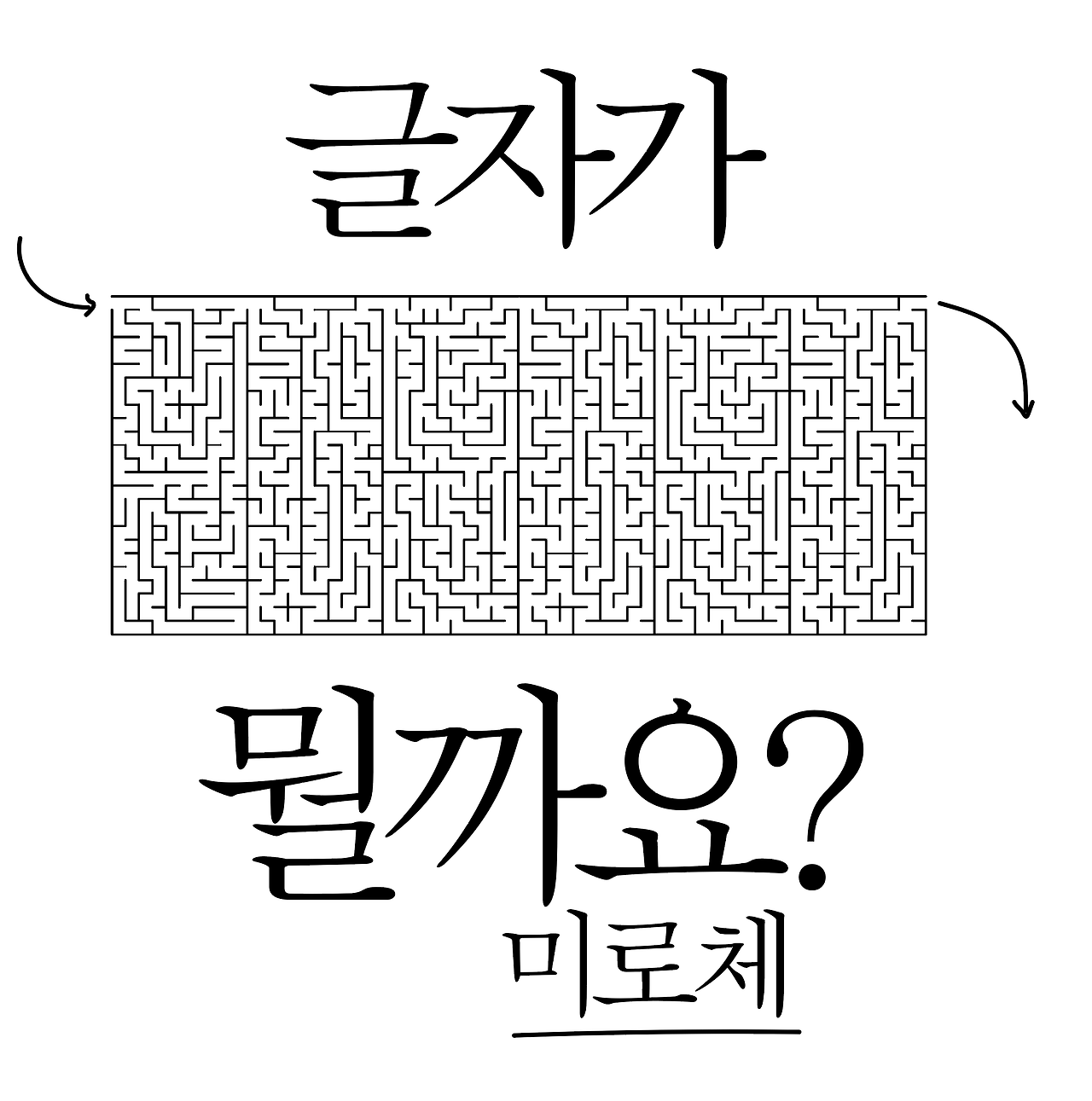
한글미로 찾기 폰트 만들기에 꽂혀서 주말반납했습니다.
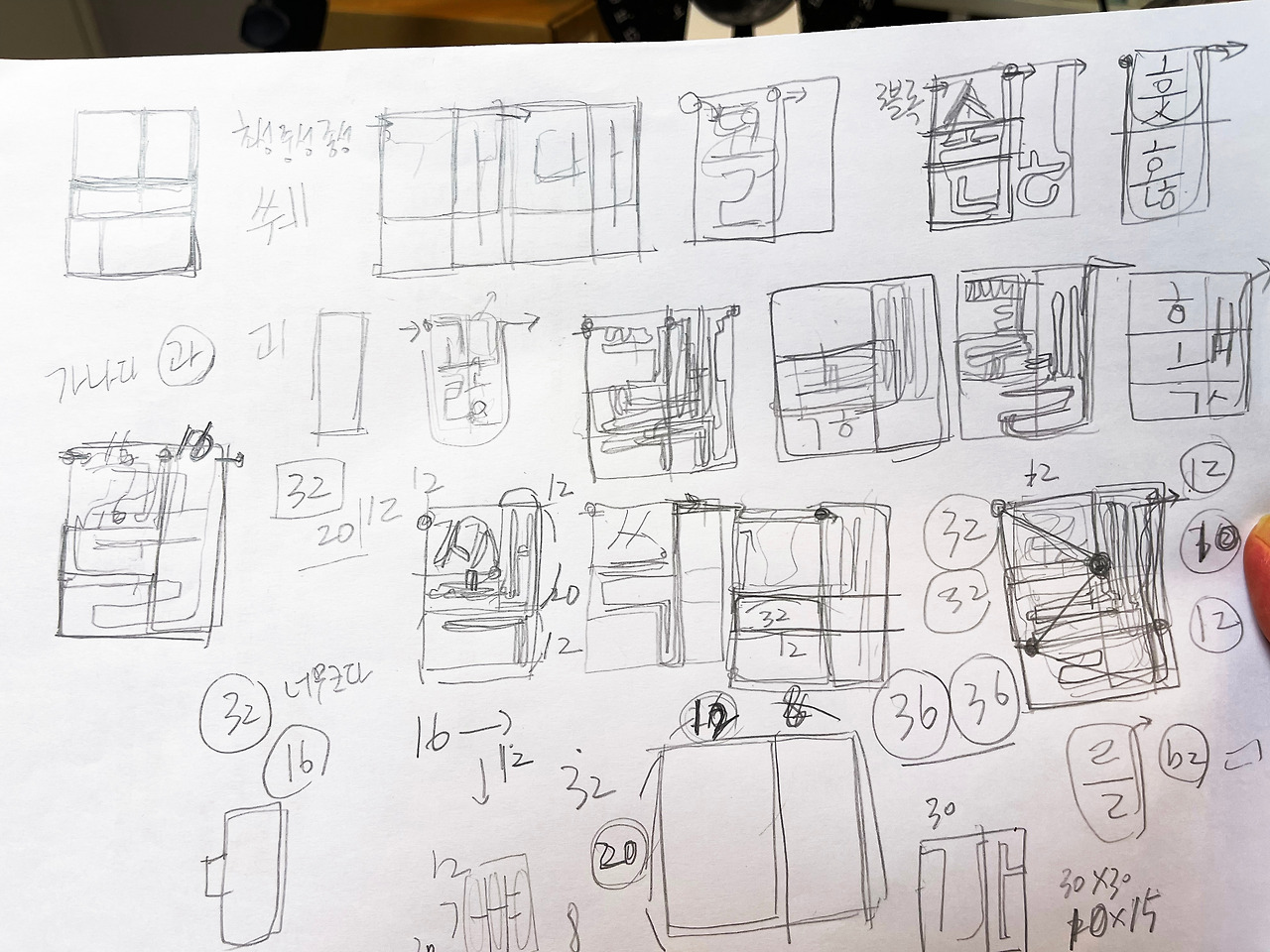
일단 조합되는 글자에 특정한 위치를 연결해서 다음 초, 중, 종성이 특정한 위치로 연결되는 글자구성을 만들었고 너비, 높이를 맞춰서 최소한의 자모를 사용해서 폰트를 만들어볼 생각이었는데… 안예쁠거 같다 라는 생각으로 다시 사각형으로 맞췄습니다.
a9미로체 폰트패밀리에 실제 폰트로 구성한 미로스타일도 준비하고 있습니다.
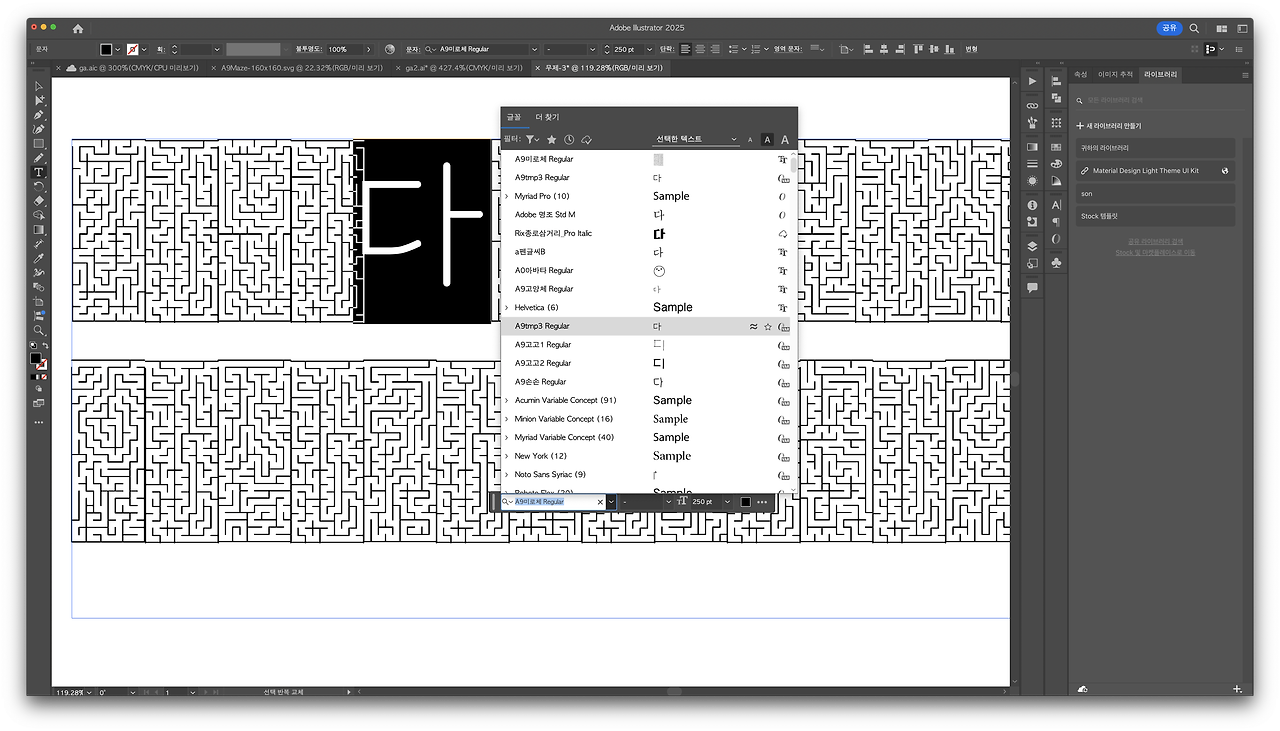
그냥 일반 한글 폰트로 바꾸면 다 자가 나옵니다.
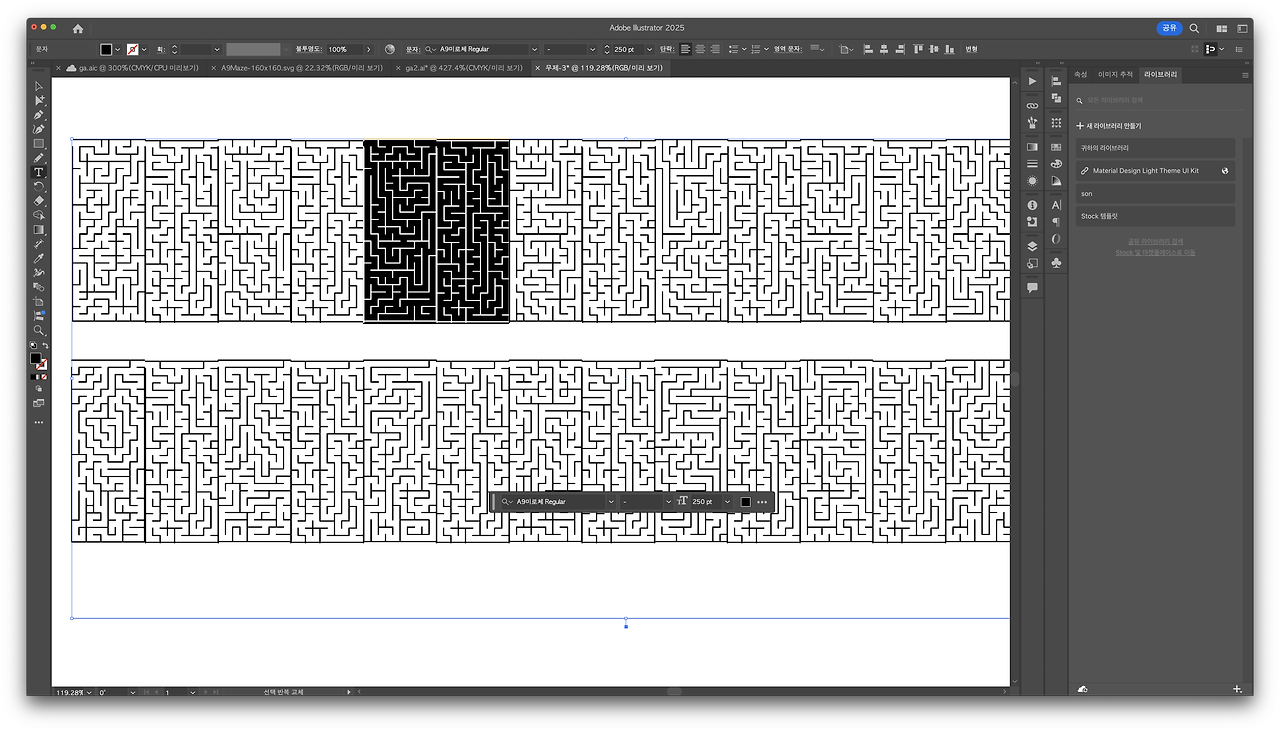
가나다라~ 하 이고 진짜 주말 날림
아주 정확하게 좌표를 잡으면 병풍느낌이나 반전했을 때 도장느낌의 글자가 될거 같습니다.
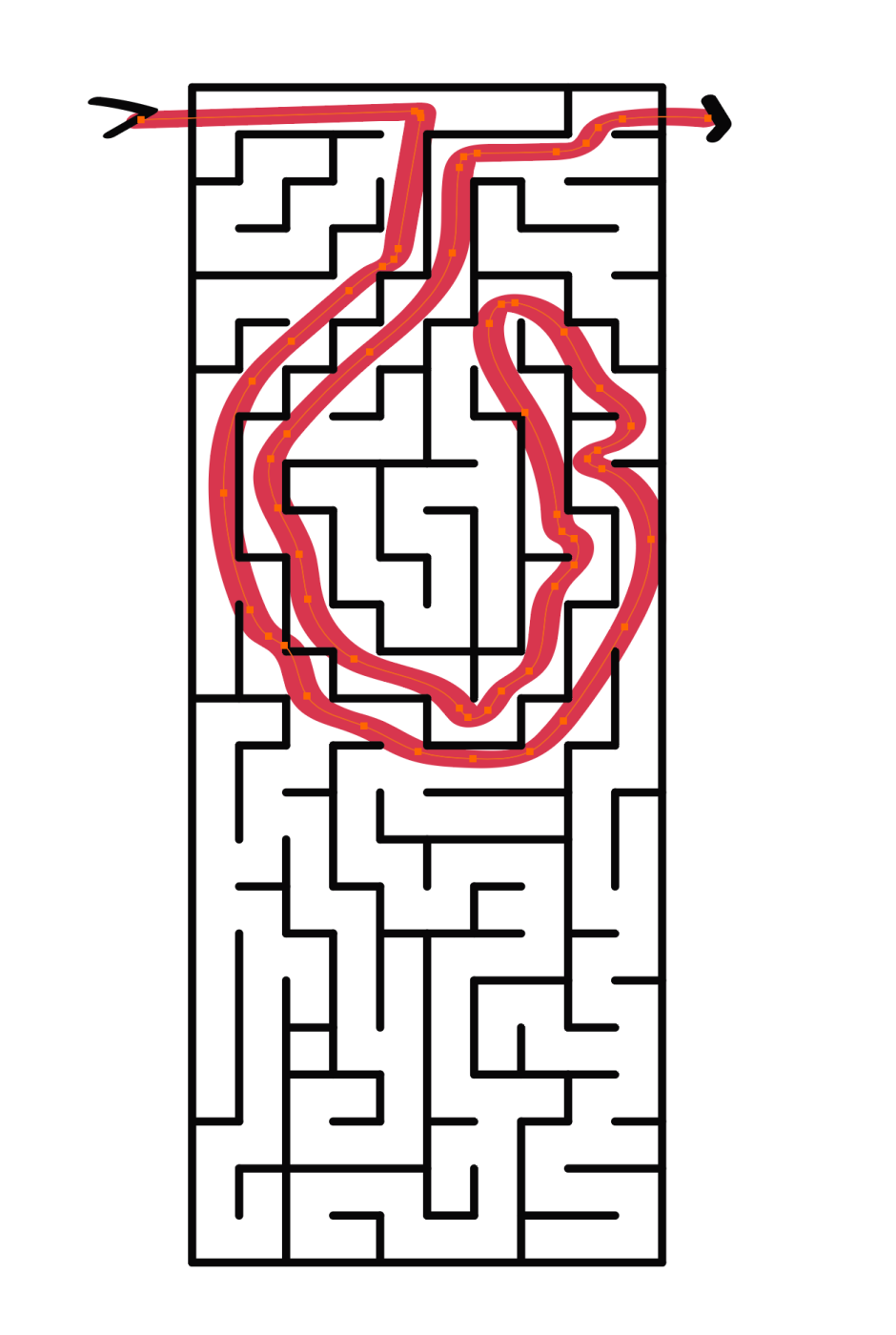
미로를 지나가서 통과하면 지나간 부분에 글자가 나타납니다. 길은 한개 앱으로 만들어서 키워볼만은 할거 같지만 지금은 먼저 다른 일부터
생각하고 프로토타입까지는 금방하지만 결과물을 위한 완성도는 아예 다른 작업이라 어린이 한글 책 내용에 넣어볼 생각입니다. ^^;;;
한글폰트의 자모음을 기반으로 한 캐릭터를 생성하고 조금 더 구체적으로 만들기 위해 얼굴 캐릭터를 다 적용해봤습니다.
일단 모양을 넣어보기는 했는데 똥모양 네모 세모 도형, 식빵 구름 모양 등 다양한 얼굴형태를 잡고 거기에 눈과 입(수염)을 적용하는 형태입니다. 전체 아이디어를 다 적용한 것은 아니라서 폰트 1개만 작업했지만 폰트패밀리가 적용될 예정입니다.
11,172자의 조합을 글자라고 하고 3자를 (3개의 다른 눈, 코, 입, 귀, 헤어 폰트) 등을 하나의 합쳐서 레이아웃을 넣고 “홍길동”을 입력하면 캐릭터가 완성됩니다.
그런 3자를 쓴 사람들을 모아주는 바보같은 커뮤니티가 됩니다. 쀲웮췕 같은 글자를 쓴다면 그걸 중심으로 그런 사람이 리스트로 검색됩니다. 일단 누군지는 모르고 2자가 겹치거나 1자가 겹치거나 조합의 일부라도 만나게 되면…
이게 뭔지 알아야 문자를 입력 하니까… 일종의 키 같은 개념의 폰트가 될거예요.
한글 배우는 외국인에게는 도움이 될지도…
이상한 생각을 하는 주말입니다.
익명인데 캐릭터로 로그인하는 방식이다 뭐 그런정도로 이해하시면 됩니다.
그냥 다른그림 찾는 게임이나 만드는게… =3=3=3
개별 수정중… 같지만 다른 애들의 개성을 만들고 맨날 다른 글자를 찾는 강박증 앱이나 어제를 기억못하면 내일 뭐가 바뀌었는지 모르는 게임…
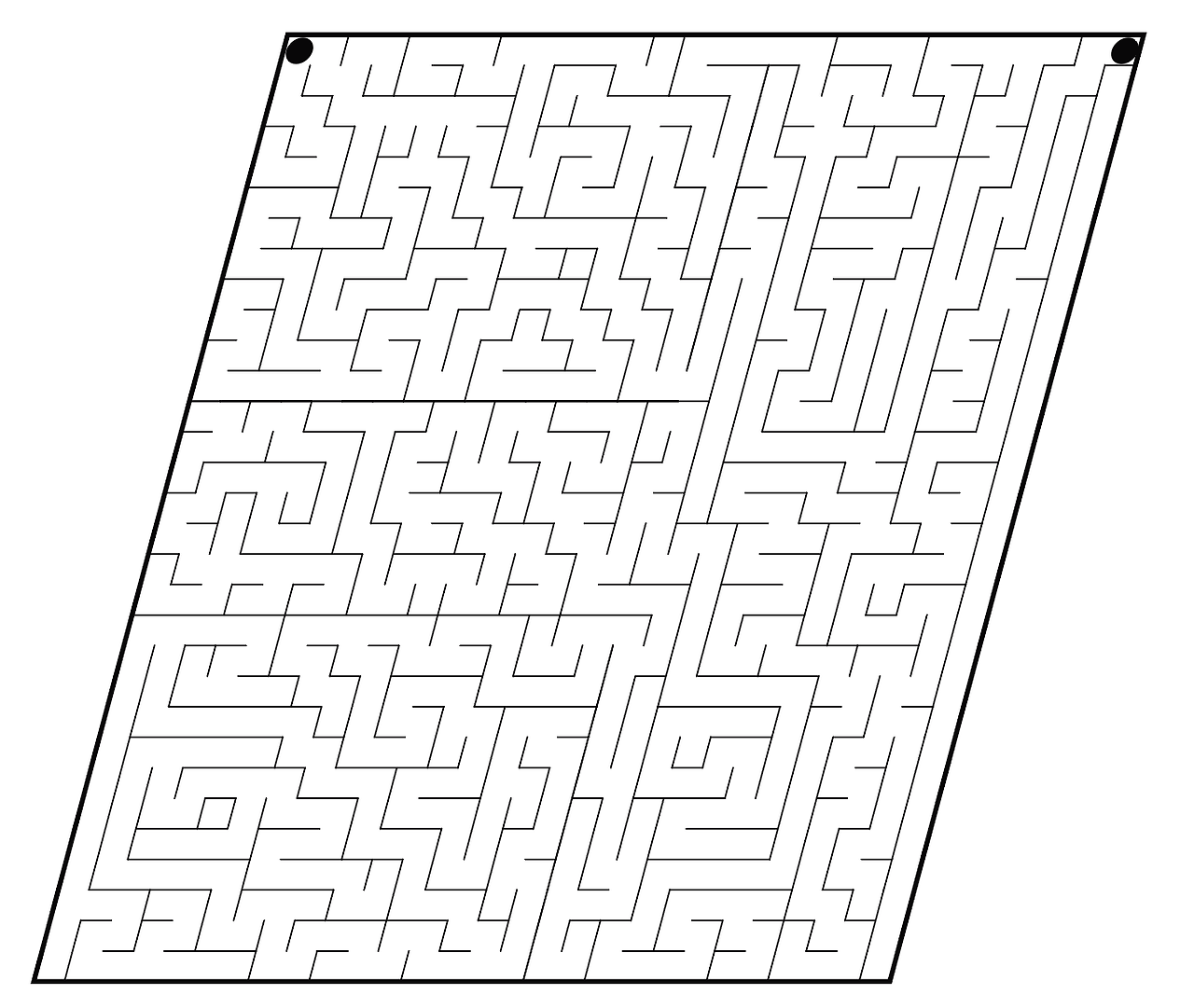
한글 미로찾기 폰트 작성중
미로를 지나간 길이 글자가 되는 미로를 만든지 오래됐다고 했는데 이미 30년 그 작업을 폰트에 적용해보기로 했습니다. (폰트 제작 초기부터 생각)
한글의 초성, 중성, 종성을 미로로 만들고 (벌수가 꽤 많음) 그걸 다시 조각내서 연결하는 방식으로 테스트해서 먼저 작성해봤습니다.
그러면 대충 이런식의 결과물이 나오는데… 제작에 대해서는 약간 다른 생각을 가지고 있어서 현재 이 버전은 프로토타입이라고 보면 됩니다. 왜냐면 직결식으로 만들면 안예쁘고 미로찾기가 재미없습니다. 맨날 똑같은 길을 지나가는 것이 목적이 아니고 새로운 길을 생성하는 방식을 찾으려고 하는 과정이기 때문입니다.
쥐도 아닌데 똑같은 길만 찾아다니면… 응?!?
하여간 길을 만들고 그 길의 패턴대로 최대한 글자를 채울수 있는 길을 만들 템플릿 제작이 우선이라서 그 다음은 조합하면 111,72자 만큼의 미로가 생성됩니다.
현재 사이즈별로 제작해야해서 18×32 로 하나 만들고 그 다음 비율별로 사이즈를 늘려갈 생각입니다. 사각형으로 만든 것도 다르게 표현할 예정입니다.
누더기를 깁어놓은 거 같은 모양이지만 테스트를 위한 것임을 보여드리기 위한 샘플입니다. 어디를 뚫고 연결하느냐에 따라 다른 미로찾기가 됩니다. 그러니까 배수관 같은 것을 틀고 닫고 하는 것에 따라 다른 미로찾기가 됩니다. 응?!?
1차 완성
이렇게 저렇게 뭔가를 하고 있는데… 정작 책만들어야 하는데 엉뚱한 일에 매진하는…
글자 나오는 미로 찾기 서울 편 – 서대문구에 대한 것을 미로 찾기로 만들고 있습니다. 미로 찾기 한 곳에 글자가 나타나게 하고 그 글자 부분에 다양한 교육정보를 보여주는 퍼즐을 만드는 중이에요.
원래는 미국의 50개 주부터 작업을 할 생각이었는데… 그냥 내가 사는 동네부터 해보자 라는 생각이 들어서 작업을 해봤습니다.
미로 찾고 찾은 미로에 글자가 나오고 그걸 맞춘 사람에게 돈을 주는 잡지를 준비하고 있었는데 그게 벌써 20년은 된 거 같습니다. 실제로 로또스도쿠라는 잡지도 창간한 적이 있었는데 결론은 모바일로 할걸 종이로 괜히 했구나 라는…
다시 게임으로 하면 좋았을까?라는 생각을 해봐도 종이로 하는 즐거움이 있는 것을 모바일로 옮겨 피곤한 게임을 만들지는 말자!
라고 생각하면서 아이패드용으로 제작 중입니다. ~
책부터 내보고 다음에 하나하나 상품성이 있는 게임으로 만들고 교육에 맞는 응? 영단어 게임이 좋겠네요. 그래야 전 세계 사람들 대상으로 하지 =3=3=3
아직 완성본이 아닙니다. 글 올리고 잠깐 작업해서 https://www.argo9.com 에 올리겠습니다.
AI가 학습할 수 있게 여러 글자체를 ㅠㅠ
미로찾고 지나가는 길이 글자가 됩니다~
조합을 늘려서 처음으로 한 벌을 온전히 만들어봤습니다.
일단 생각하는 것과 조금 달라지긴 했지만 조합은 많아졌는데 쓴 기본 글자 갯수는 반복되어 더 적은 갯수로 만들어봤습니다.
표지에 들어간 레터링을 현재 기계용이 아닌 본격 폰트로도 제작합니다.
폰트로 만든 11,172개 숨은그림 찾기의 새로운 캐릭터
이번에 한글 폰트 조합을 이용해서 캐릭터를 만들기로 했습니다. 지금은 샘플이라 대충 아이디어만 구현했습니다. 아이들 집중력을 키워주는 수 많은 캐릭터들이 겹치지 않고 나오게 할 생각으로 조합해서 만들고 있습니다.
각종 도형위에 눈, 코, 입 그리고 몸을 따로 붙여서 css 로 폰트와 의상, 악세서리 등등 수조개의 조합이 나올 수 있게 구현하고 있습니다.
20대에 아바타, 미니홈피 회사에서 개발을 했고 플래시관련 솔루션을 했던 경험을 이쪽에 녹여서 기술에 대한 부분을 요즘에 맞춰 바꿔보려는 시도중 하나입니다.
폰트에 사용하는 코드는 1,114,112 개 그리고 폰트는 패밀리 벌수 추가하면 수없이 늘려갈 수 있습니다.
이제 같은 친구 찾기 게임을 만들고 움직이는 기능도 포함할 생각입니다.
어린이, 어른이 용 다양한 퍼즐게임… 못찾으시려나 =3=3=3